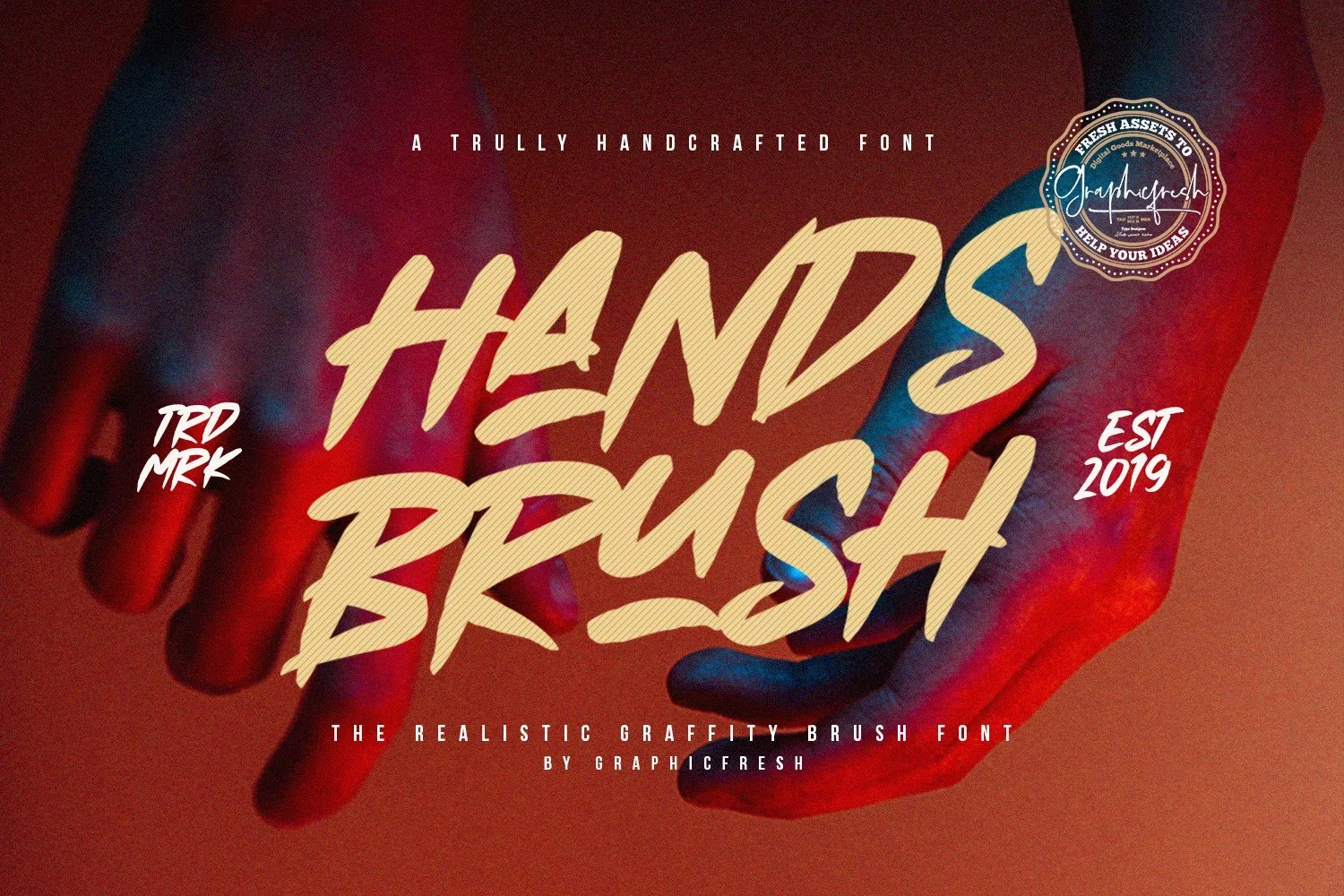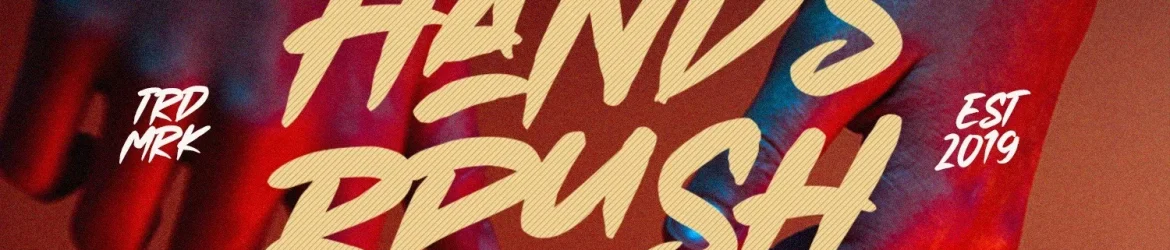
Esta é uma bela fonte de display com estilo de pincelada à mão. Foi criada pelo font designer Graphicfresh. O Hands Brush oferece uma mensagem clara e rápida, perfeitamente adaptável para uso em logotipos, roupas, frases ou embalagens de produtos, quando um boost de tipografia é necessário. Este estilo pincelado realista vai enriquecer seu design, tornando-o mais atraente sem perder a sua personalidade única. Ideal tanto para criar uma identidade visual forte quanto para expressar emoções fortes e dinâmicas em seus projetos. Descubra o poder do Hands Brush e renove suas criações com um toque de originalidade e força.